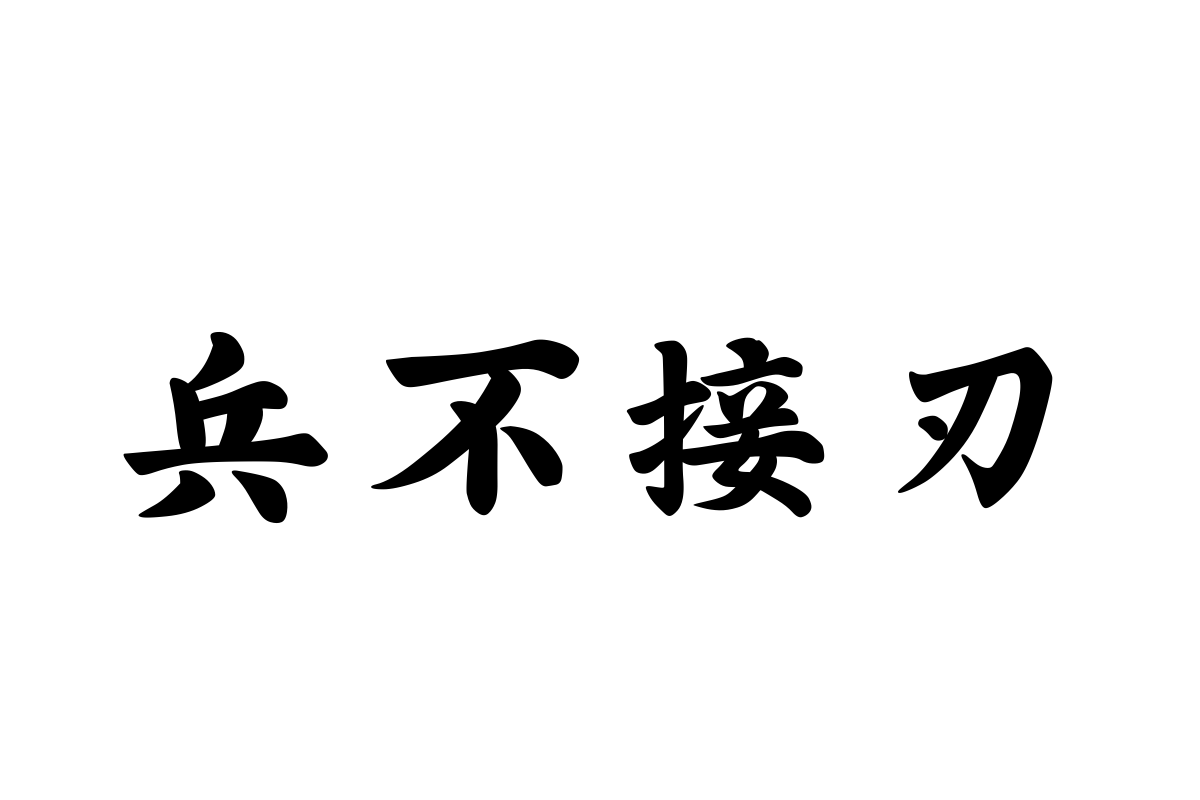
千字文是中国古代著名的启蒙读物,由周兴嗣编纂。它以四字一句、两句一组的形式,共一千零一个字,涵盖了天文、地理、历史、文化、道德、哲学等多方面的内容。千字文的字体特点如下:
1. 字形规整:千字文的字形规整,笔画清晰,易于辨认。每个字的笔画顺序和结构都有一定的规律,使得整篇文章看起来整齐划一。
2. 字体大小适中:千字文的字体大小适中,既不会显得过于拥挤,也不会显得过于稀疏。这使得读者在阅读时能够轻松地把握文章的节奏和节奏。
3. 字体风格统一:千字文的字体风格统一,没有明显的繁体字和简体字之分。这使得读者在阅读时能够更加专注于文章的内容,而不是字体的外观。
4. 字体易读性强:千字文的字体易读性强,没有过多的装饰性笔画和复杂的结构。这使得读者在阅读时能够更加专注于文章的内容,而不是字体的外观。
总之,千字文的字体特点在于规整、适中、统一和易读性强,这些特点使得千字文成为了古代启蒙读物中的经典之作。